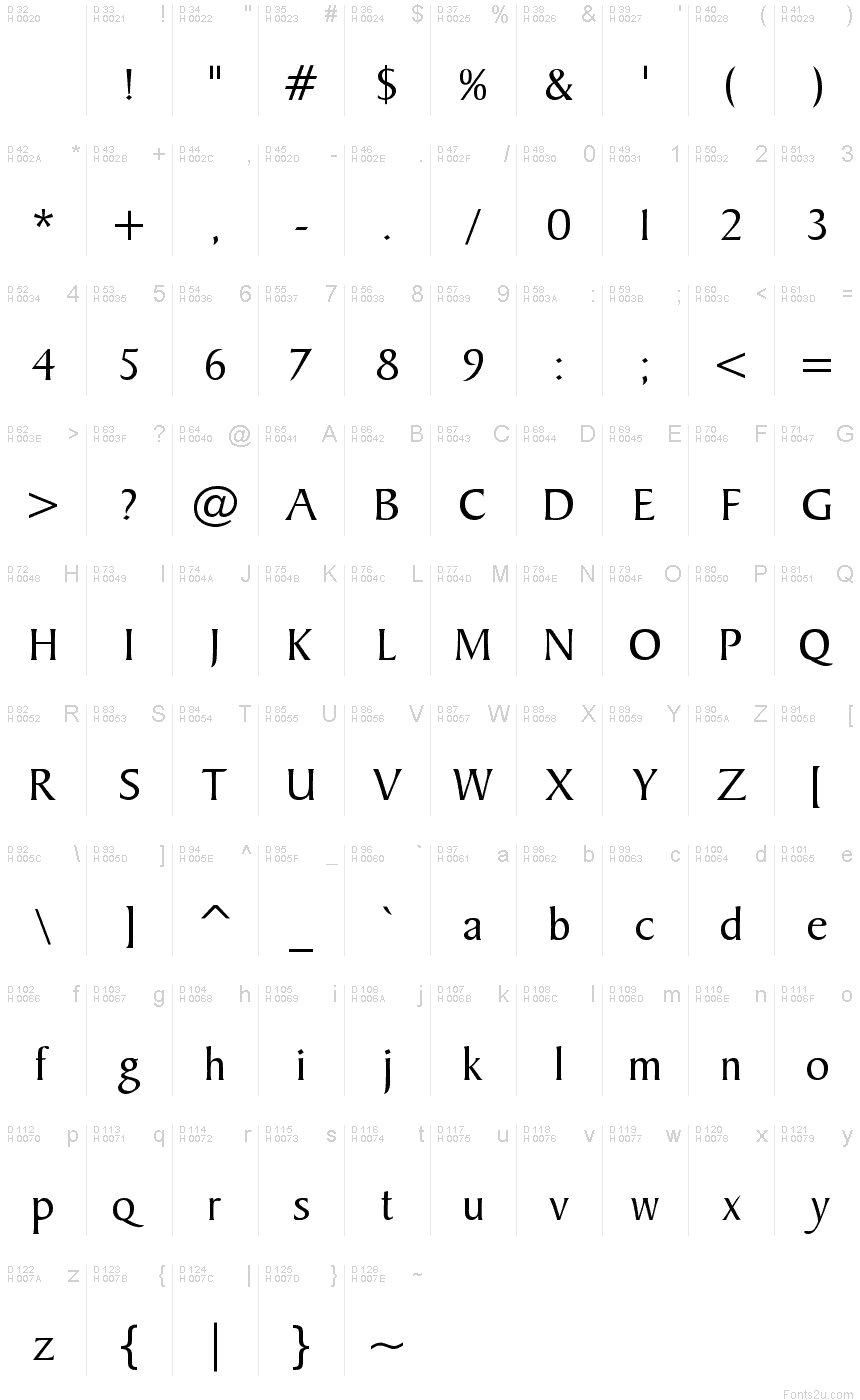
Barrett Normal
Barrett Normal od Bay Animation to darmowy krój szeryfowy z cichą pewnością siebie dobrze wydanej książki. Litery sprawiają wrażenie rysowanych tuszem, a nie projektowanych mechanicznie – miękkie krzywizny przechodzą w mocne, lekko rozszerzone szeryfy, dzięki czemu tekst jest uporządkowany i czytelny. W ramach rodziny Barrett rytm pisma jest stabilny i zwarty, co nadaje tekstowi literacki, niemal drukarski charakter, nie sprawiając wrażenia sztywnego czy przestarzałego.
Jako darmowy font, Barrett Normal doskonale sprawdza się w składzie redakcyjnym, wnętrzach książek, na literackich okładkach, w identyfikacjach wizualnych produktów premium, opakowaniach z nutą tradycji oraz na klasycznie zaprojektowanych stronach internetowych. Subtelna osobowość jej krzywizn dodaje ciepła zaproszeniom i programom, nie odciągając uwagi od treści. Aby uzyskać zrównoważony wygląd, połącz Barrett z czystym geometrycznym krojem bezszeryfowym w podpisach i elementach interfejsu, a samą Barrett wykorzystaj do nagłówków i średniej wielkości tekstów.